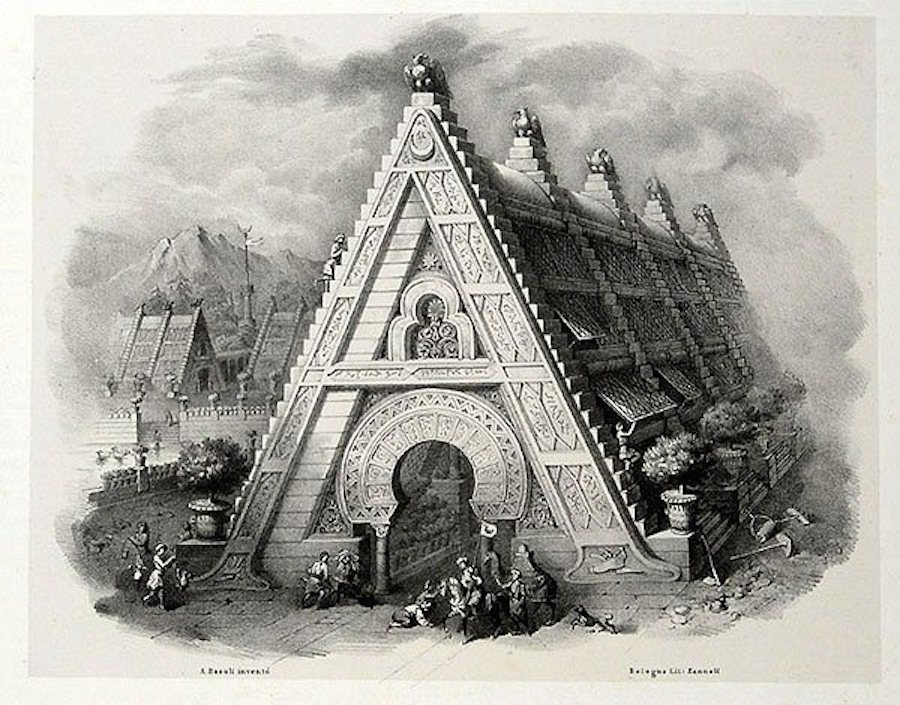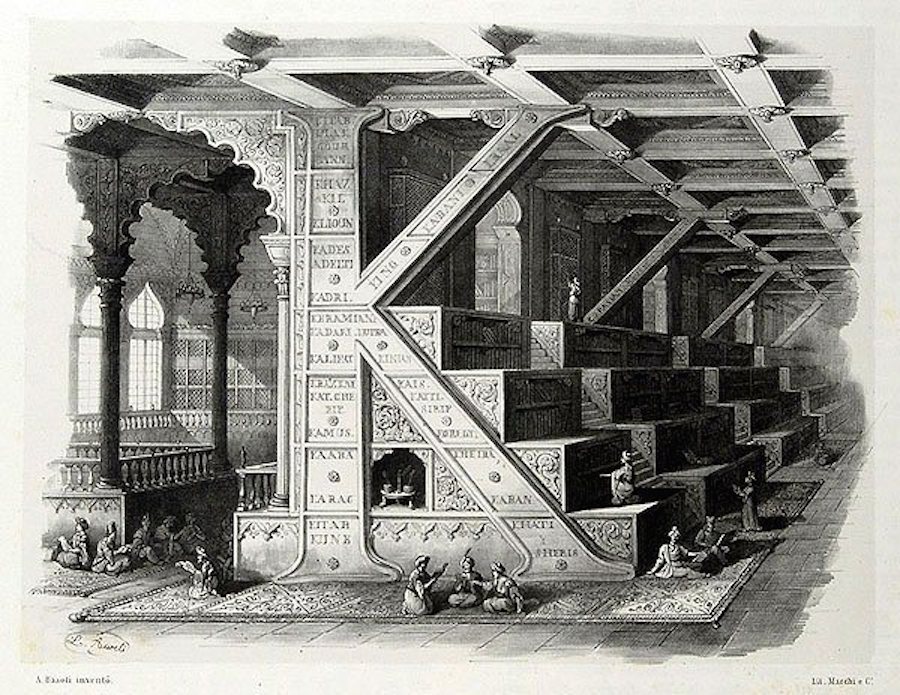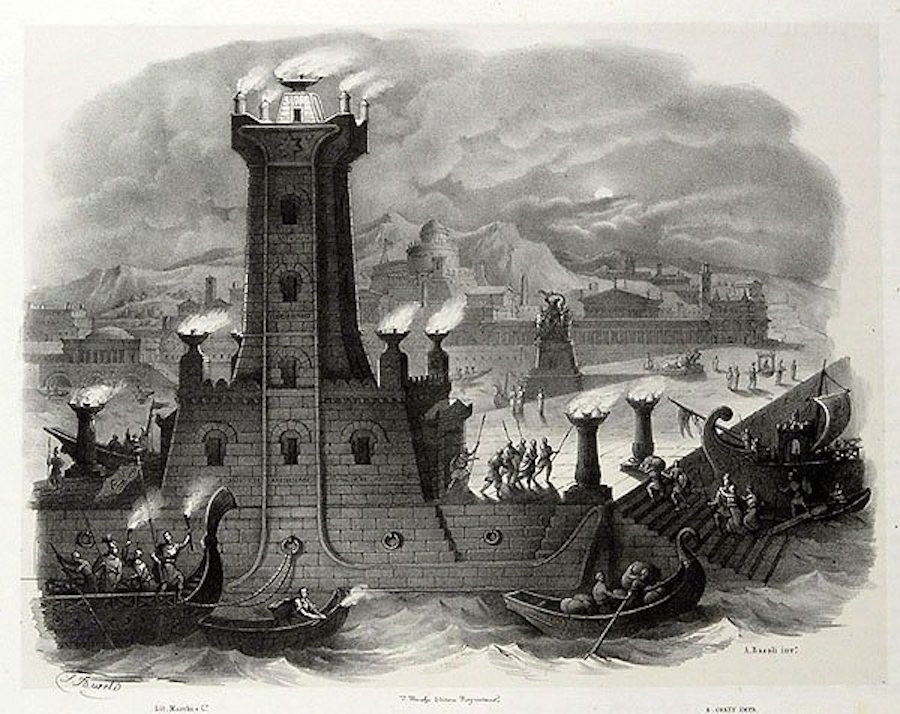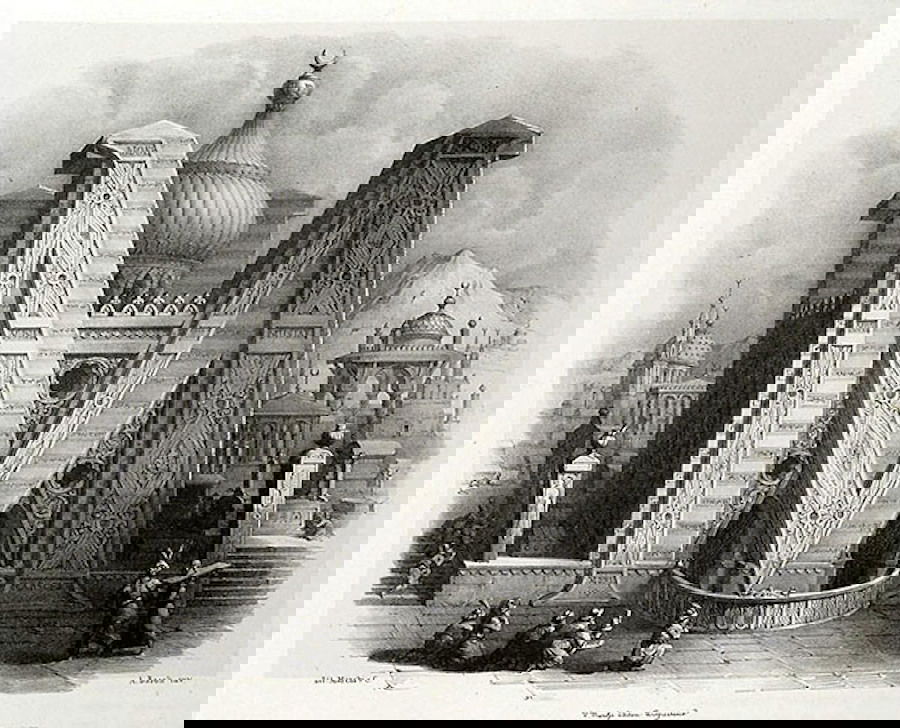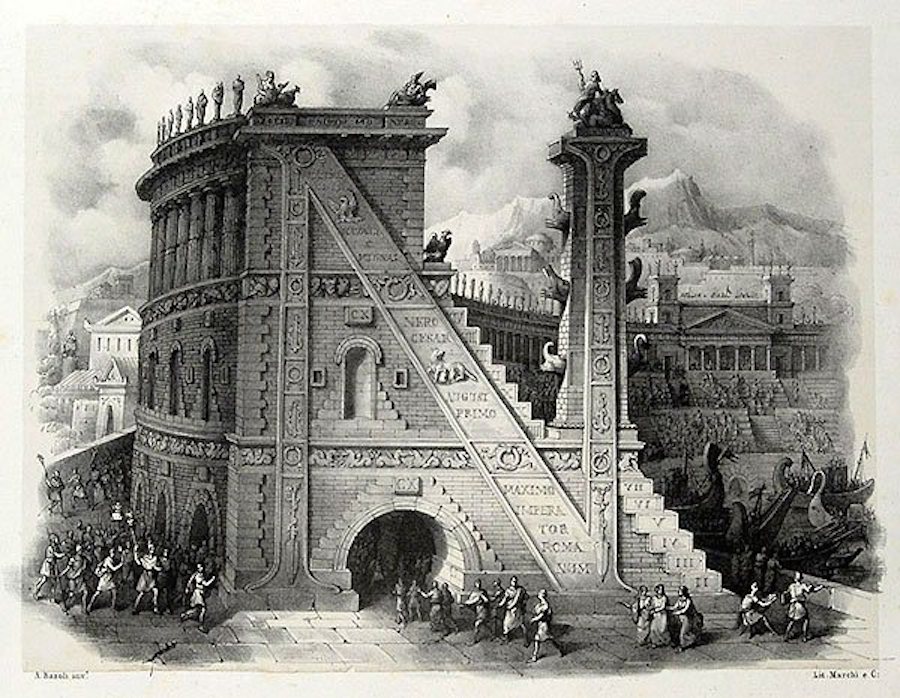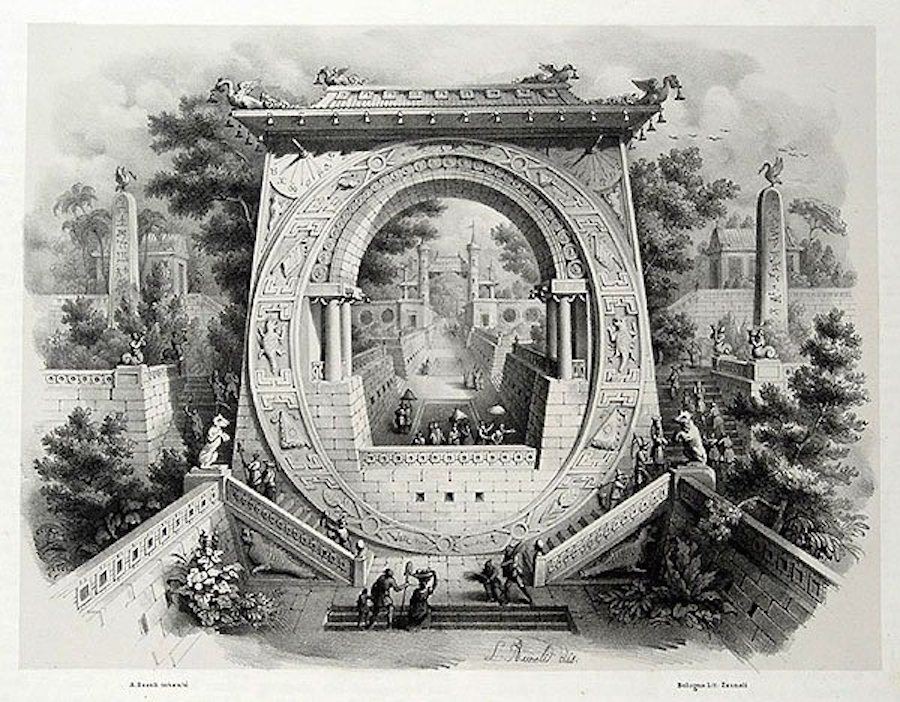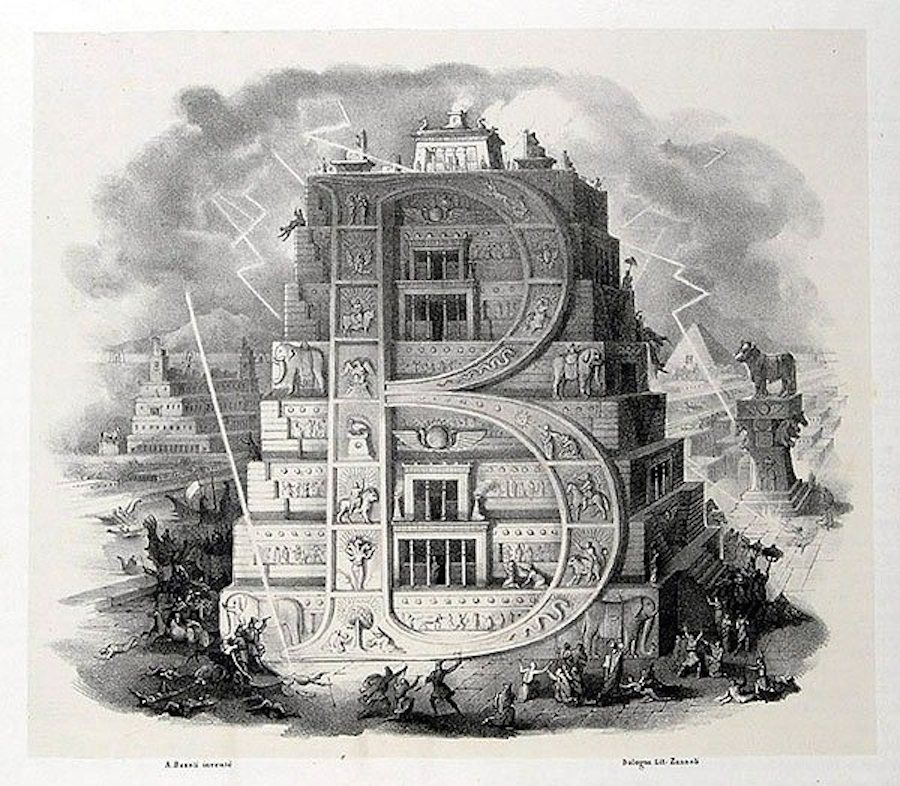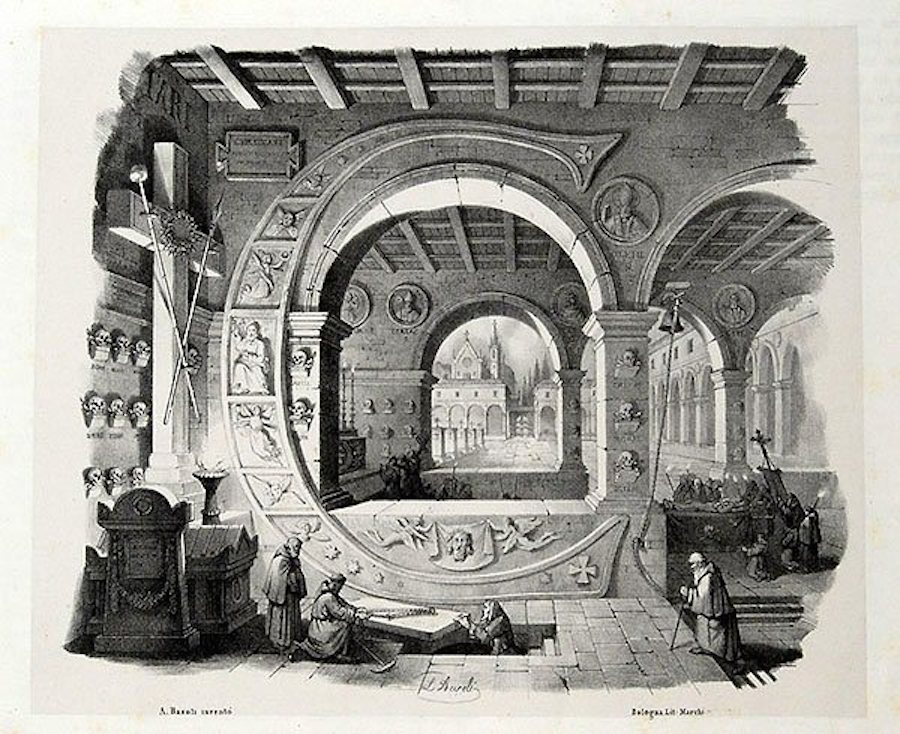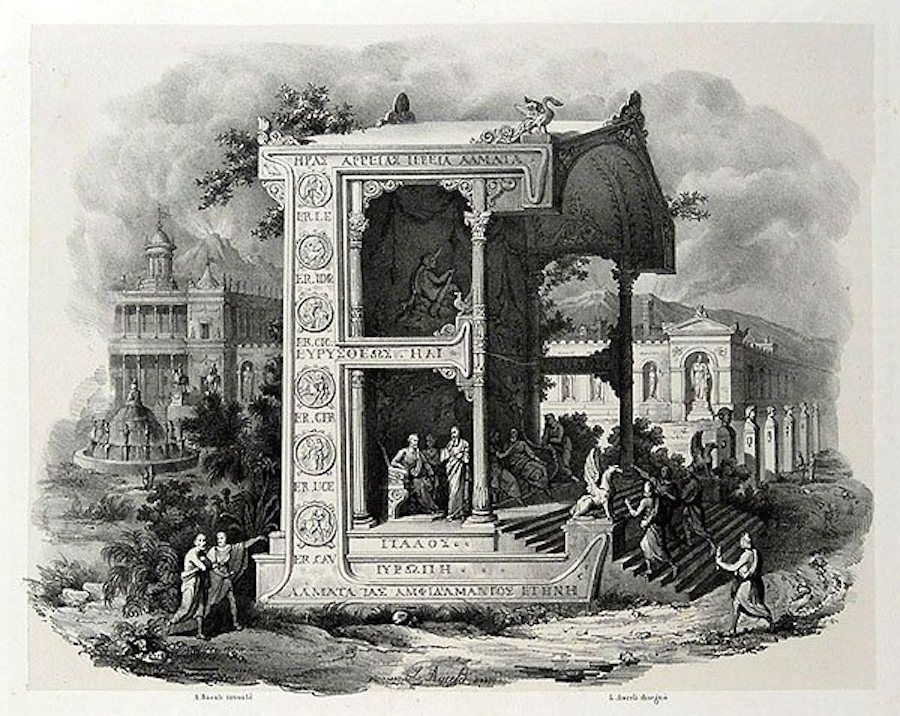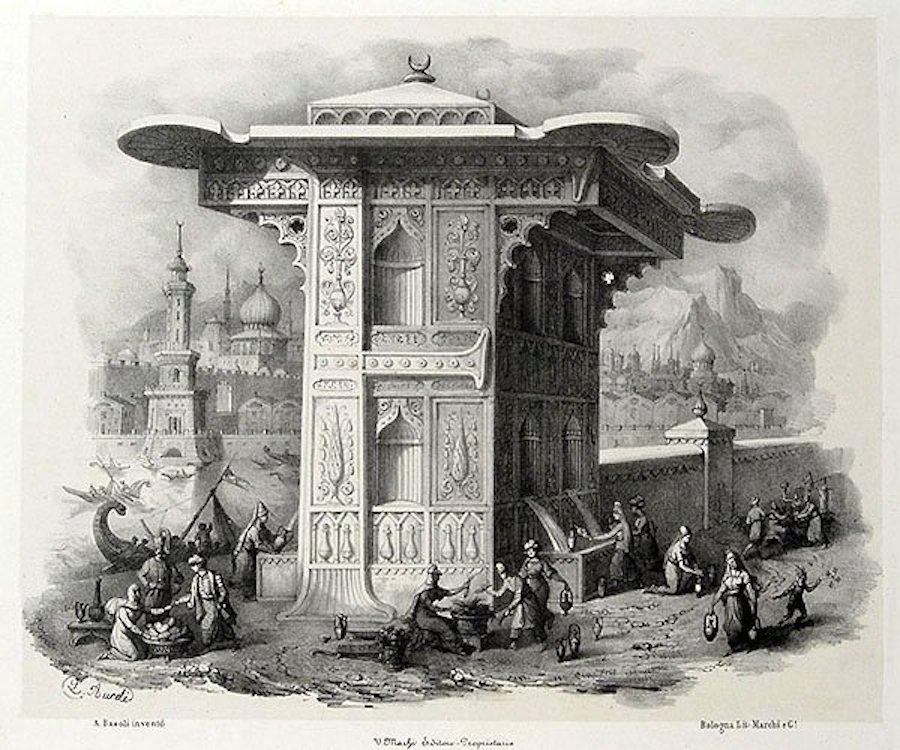
En el siglo XIX las tipografías tenían forma de castillo
Más de un diseñador computarizado de los de hoy, probablemente, se negaría a confesar a qué se dedica si la cuestión se la hiciera el fantasma de Antonio Basoli. Este interiorista boloñés que vivió de 1774 a 1848 no necesitaba ser de la era de las tipografías de mouse para marcarse un trabajo de alto detalle alfabético.
En 1839 publicó un conjunto de litografías para su libro Alfabeto Pictórico, que en versión original se llama Alfabeto Pittorico, ossia raccolta di pensieri pittorici composti di oggetti comincianti dalle singole lettere alfabetiche.
Ilustración a ilustración, en total el italiano donó a la posteridad una serie de 24 letras y un símbolo que recupera hoy Retronaut. La razón por la que aún resultan innovadoras es porque no es tan sencillo dibujar a mano un abecedario representado en edificios con arquitecturas clásicas y orientales de detalles milimétricos.
Tras ser alumno aventajado de la Academia de Bellas Artes, Basoli decoró palacios como el Ercolani o el Palazzo Baciocchi y villas como la de Marescalchi. Incluso se animó a publicar un tratado de decoración doméstica en 1827. Aunque su verdadera devoción era poner de punta en blanco el interior de los teatros, llegó a hacerlo incluso en la Scala (Milán).
Dicen sus biografías que prefería que los decorados entre telones fueran oníricos. Lugares donde cupieran, por ejemplo, letras con forma de castillos.